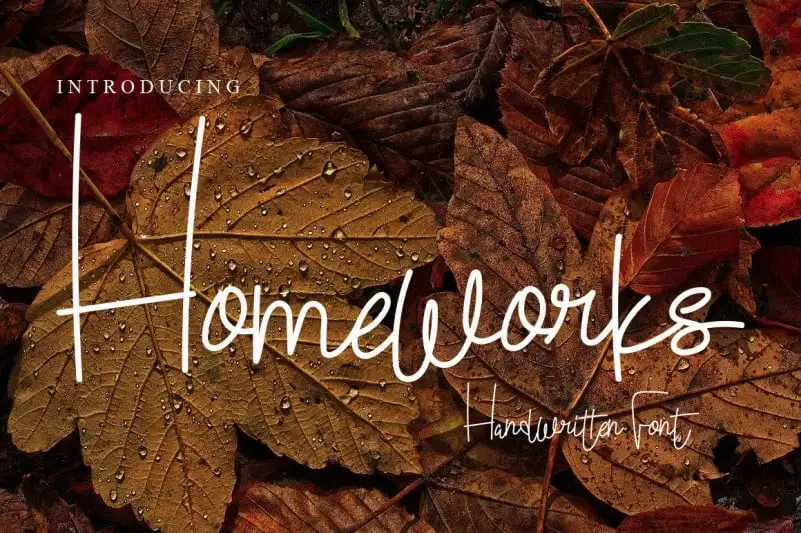
Homeworks Handwritten Font – Download Grátis
A Homeworks Handwritten Font é uma elegante tipografia script com um tema relaxado, apresentando um estilo encantador que a torna perfeita para quem busca personalidade e sutileza em suas criações digitais. Este font delicado não apenas combina perfeitamente para seus trabalhos pessoais ou profissionais, mas também pode ser o ponto de brilho que você está procurando para decorar sua biblioteca de fontes. Seja para um projeto de texto casual ou uma impressão de arte sofisticada, a Homeworks Handwritten Font certamente dará um toque único e encantador à sua produção. Esta elegante font escrita à mão pode ser usada em diversos contextos e é perfeita para aqueles que buscam diversidade e personalização nas suas criações digitais.